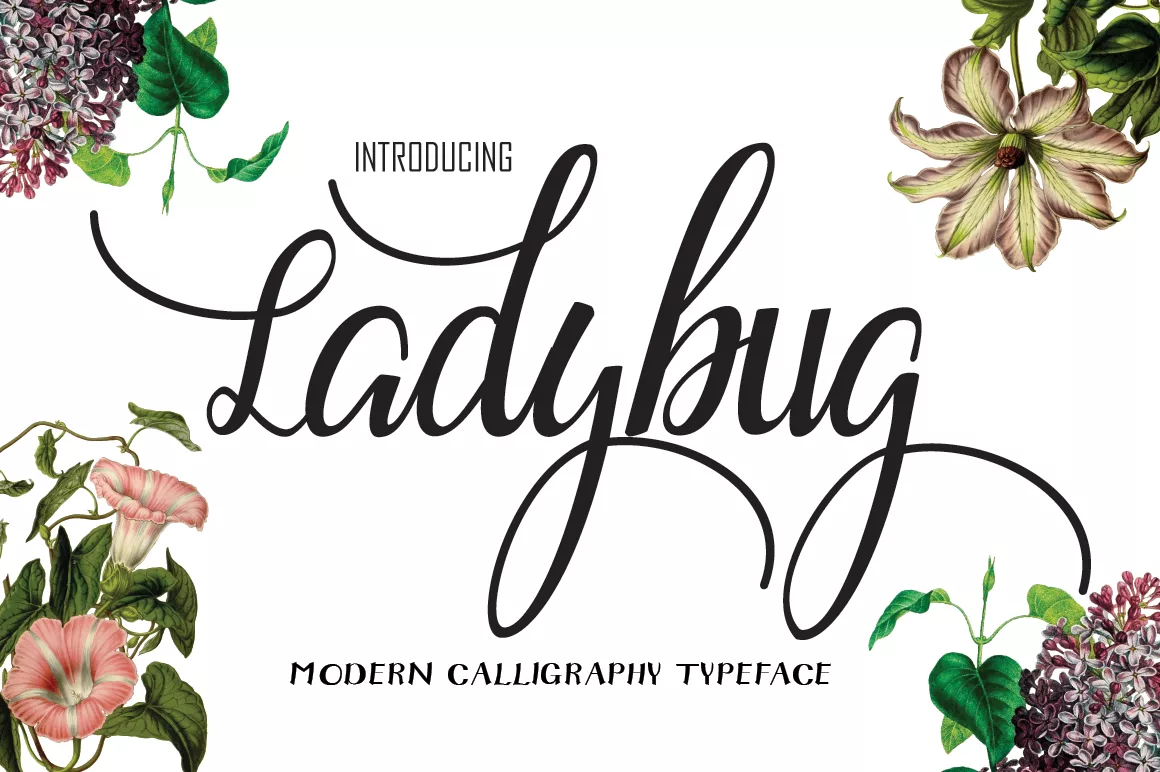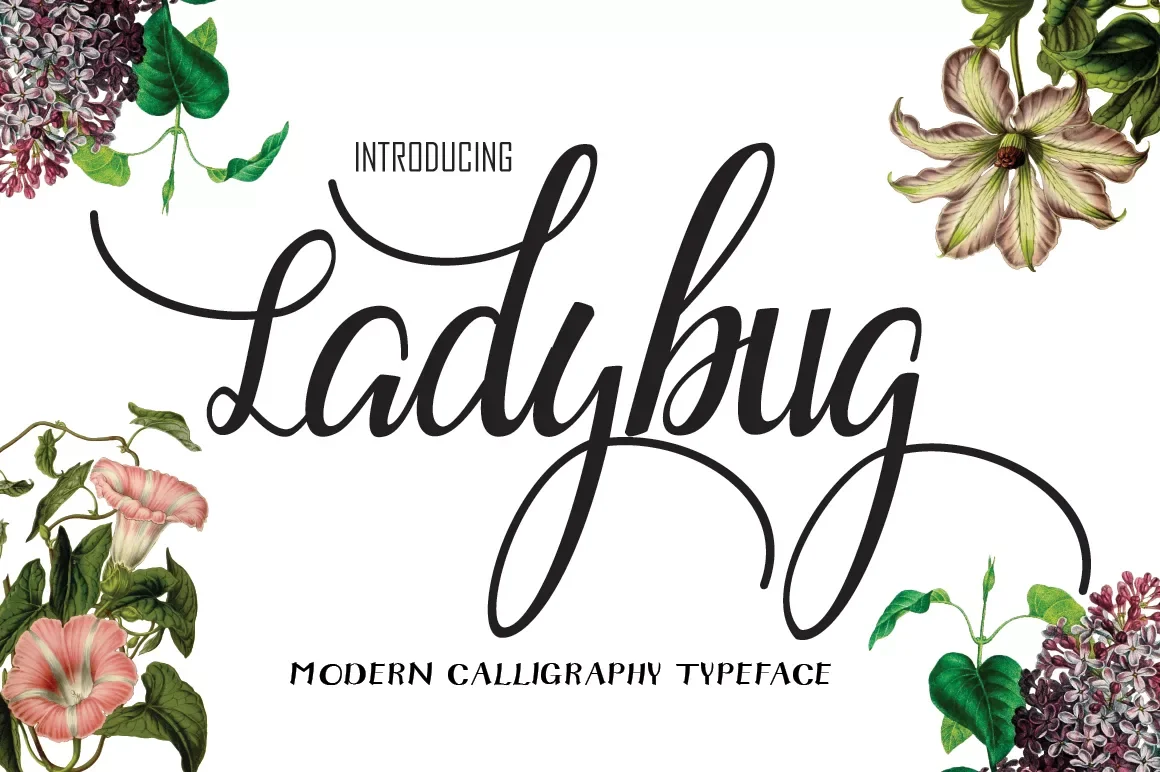
Название: Ladybug Font (2021)
Божья коровка - это шрифт жирный, красивый и уникальный, он является образцом современных каллиграфических шрифтов в сочетании с каллиграфическим стилем письма.